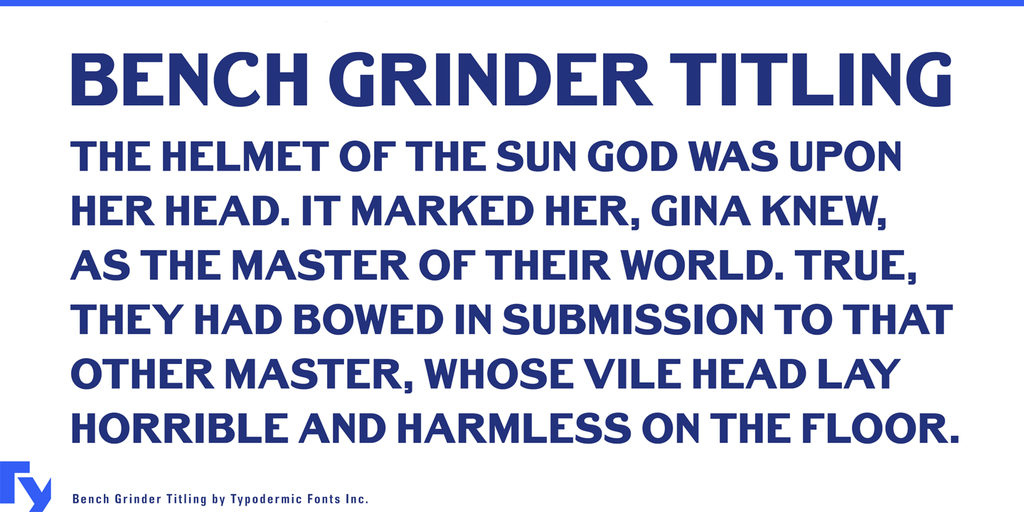
Bench Grinder Titling Font
Bench Grinder é uma nova adição à família das fuentes sans serif do typodermicfonts.com, inspirada no estilo dos títulos metalhead do século XIX mas sem as serifas largas que proporcionam um acabamento mais robusto. A fonte mantém os traços finos e leves característicos do sans serif, oferecendo uma personalidade única e desafiadora, mesmo assim manejando um aspecto familiar que pode torná-la bastante versátil para múltiplas aplicações visuais. Se você está procurando uma fonte sem serifa com letras minúsculas também disponíveis, não hesite em dar uma olhada na versão regular de Bench Grinder. Este projeto inspirado no trabalho dos tipógrafos do passado moderniza o conceito, oferecendo um estilo único e emocionante que é adequado tanto para uso cotidiano quanto para trabalhos de design gráfico avançados.